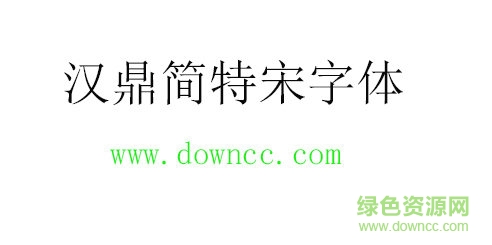
漢鼎簡(jiǎn)特宋-普通是一款常規(guī)的宋體字體,寫(xiě)法大方,非常適合于文章書(shū)寫(xiě)、藝術(shù)設(shè)計(jì)等等方面,它能讓你在設(shè)計(jì)畫(huà)面廣告信息時(shí)的字體更加突出有亮點(diǎn),還能應(yīng)用于圖片文字設(shè)計(jì)等多個(gè)方面哦,有需要的朋友可以來(lái)綠色資源網(wǎng)免費(fèi)下載哦!